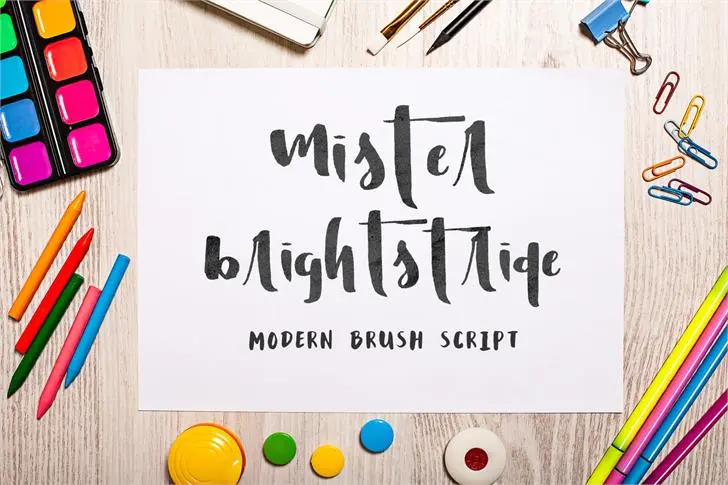
A Mister Brightstride é nossa primeira tipografia feita sob a forma de escrita cursiva chamada calligrafia a esfumar. Ela foi criada usando uma caneta Tombow Dual Brush, fornecendo letras com um ar de muita atitude. As linhas de base variam entre as letras maiúsculas e minúsculas, e algumas letras minúsculas são alternativas. A fonte também foi ajustada em espaçamento para melhorar a impressão visual de todos os seus projetos. Ideal para quem quer dar um toque especial às suas criações, seja em projetos de design gráfico ou escrita manuscrita, essa fonte é uma ótima escolha.